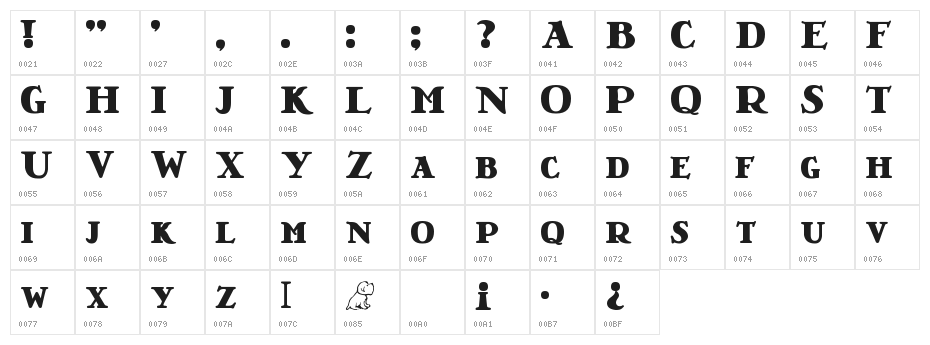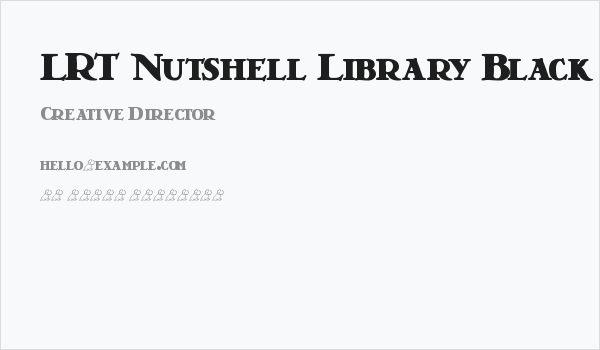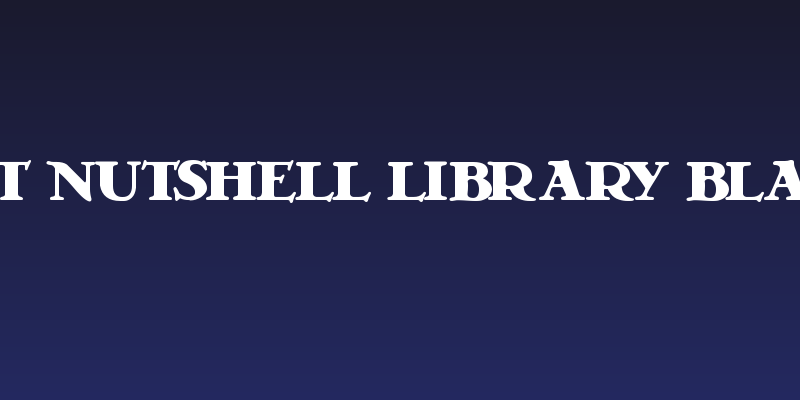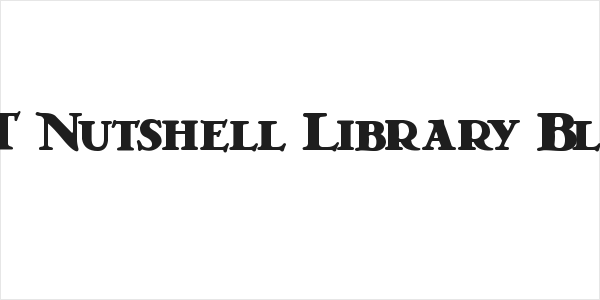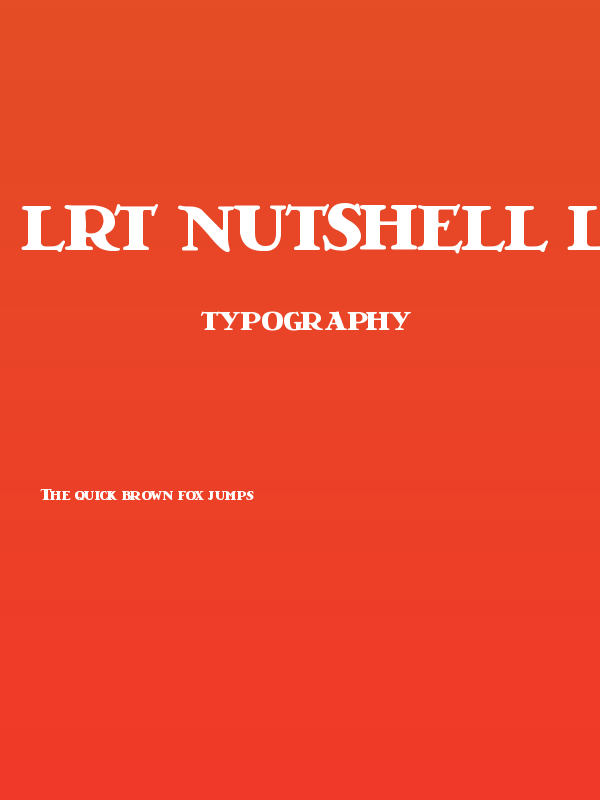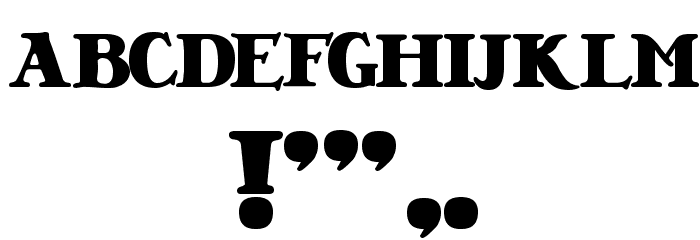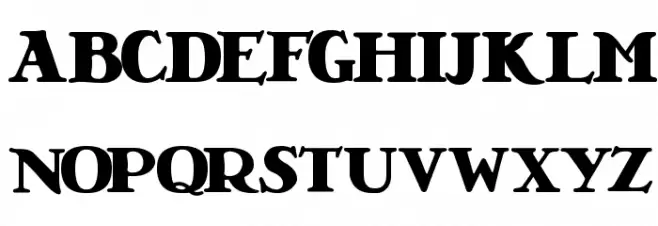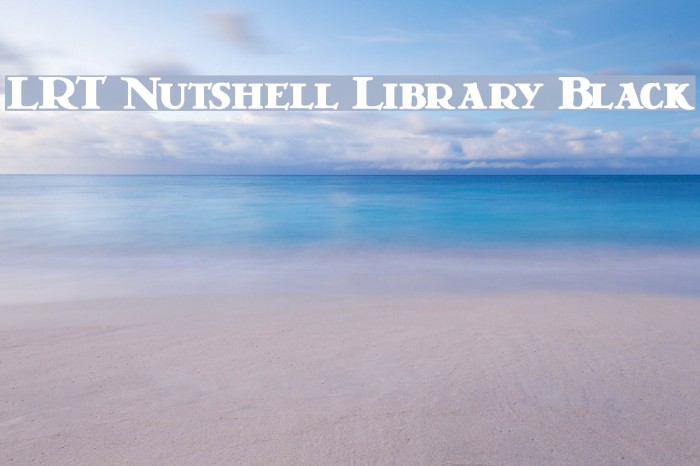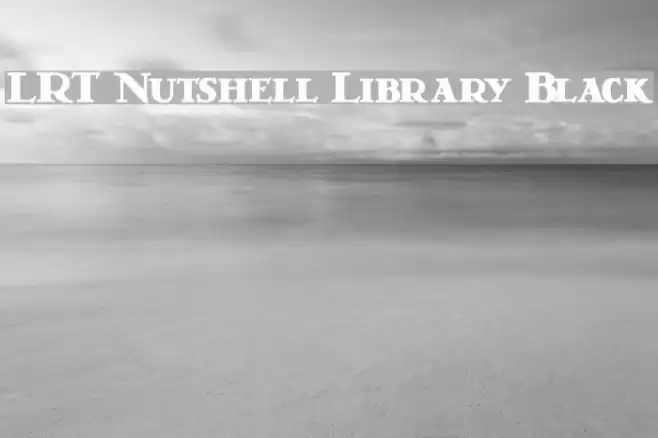
LRT Nutshell Library Black Font
| النمط العام | Classic |
| مشاريع مقترحة | This font is perfect for projects that require a strong visual impact, such as posters, book covers, branding materials, and editorial headlines. |